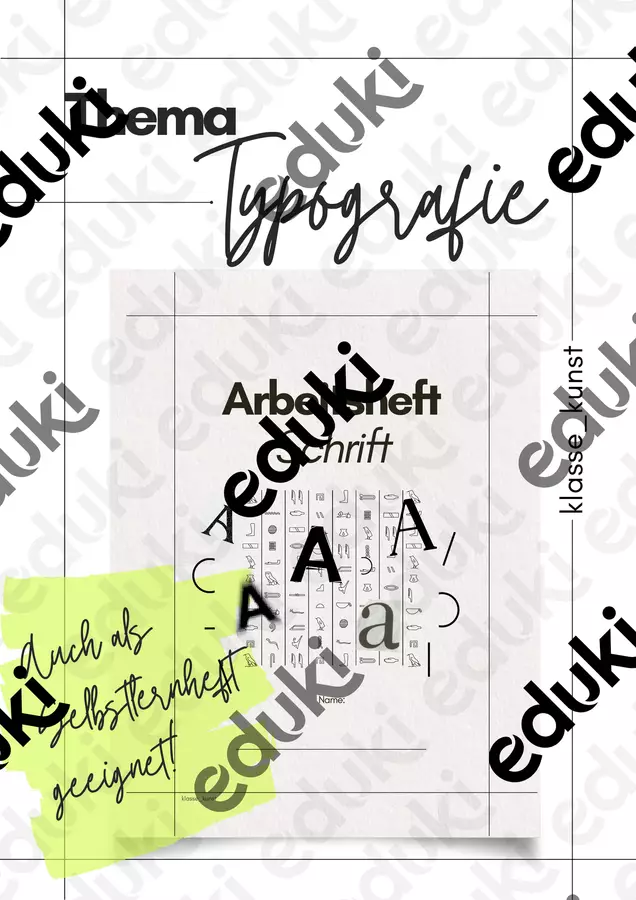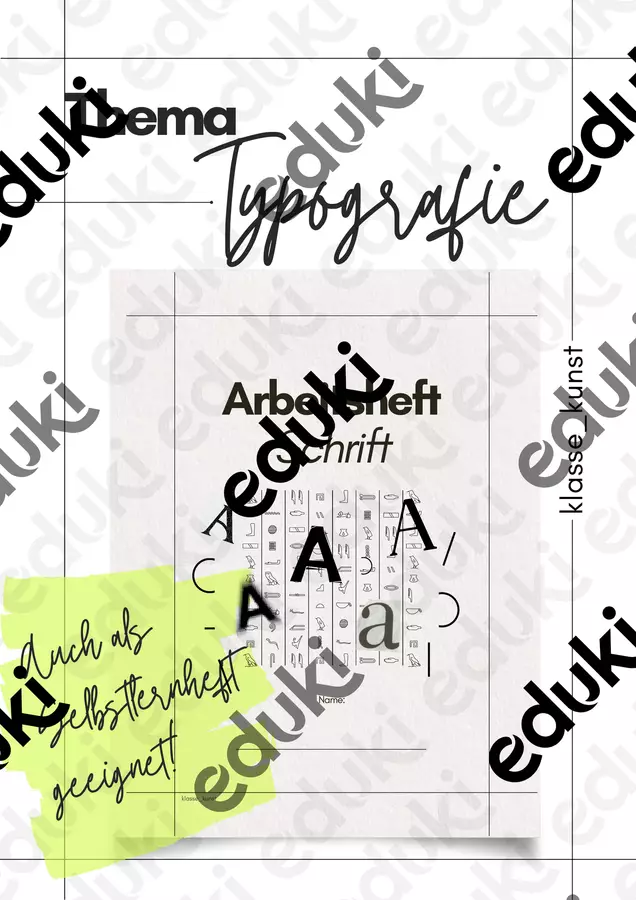
Stundenentwürfe - Typografie in der Grundschule - Arbeitsheft Schrift - klasse_kunst  - Deckblatt
Dieses Arbeitsheft eignet sich als Selbstlernheft und gibt Kindern ab Klasse 3 die Möglichkeit, sich dem Thema Typografie anzunähern.
Inhalt:
• Hieroglyphen - Schreiben wie im alten Ägypten
• Die Bausteine unserer Schrift
• Geschmückte Schrift - Was macht eine Schrift besonders?
• Das ABC der ... - das Alphabet gestalten
• Schrift fühlen - Punktschrift - das Braille Alphabet
• verschiedene Kreativaufgaben
Typografie in der Grundschule - Arbeitsheft Schrift